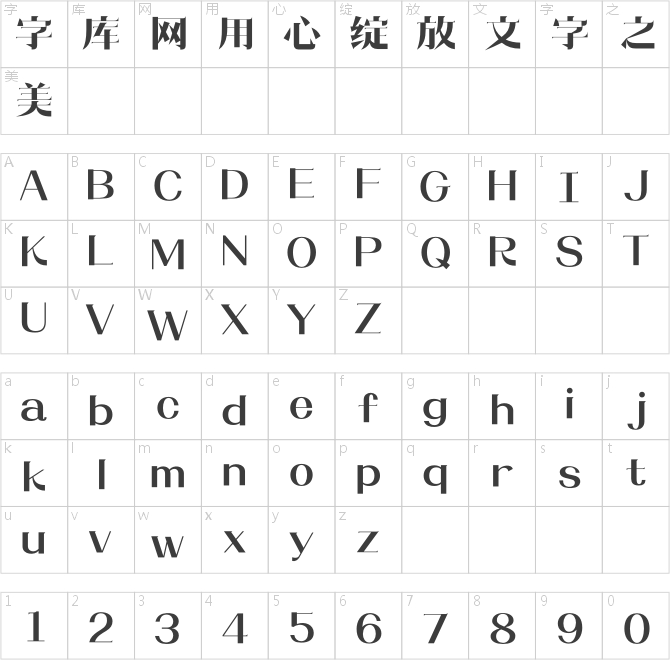
造字工房松風(fēng)體
造字工房
造字工房松風(fēng)體,結(jié)構(gòu)規(guī)整典雅、橫豎筆畫對比強(qiáng)烈,筆畫尖角自成風(fēng)格,輕盈蜿蜒,字形剛?cè)岵?jì),橫、撇、捺的個性處理,使其呈現(xiàn)出沉靜閑適和變化豐富的色彩。適用于大標(biāo)題及個性品牌設(shè)計(jì)推廣等環(huán)境。